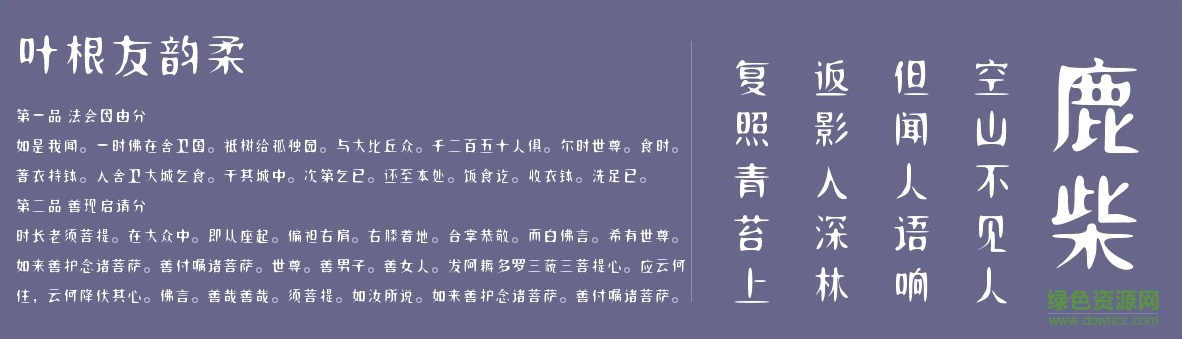
葉根友韻柔
葉根友韻柔字體是一款由知名書法家葉根友創(chuàng)造的字體,比劃圓潤,適用于廣告、藝術(shù)設計,海報設計等方面,有需要的朋友們不要錯過了。歡迎大家來綠色資源網(wǎng)踴躍下載哦!
葉根友微剛韻柔是一款表達圓潤思想的字體,取自中國東方圓潤之美的韻律,吸取中國漢字獨有的結(jié)構(gòu)表現(xiàn)特質(zhì),雍容華貴的體現(xiàn)了書法字體的美好一面。
葉根友韻柔字體,用途廣泛,是葉根友先生的印刷字體,適合場合很多,字體看起來比較柔和、舒適。各位字體收藏者可以來看看。